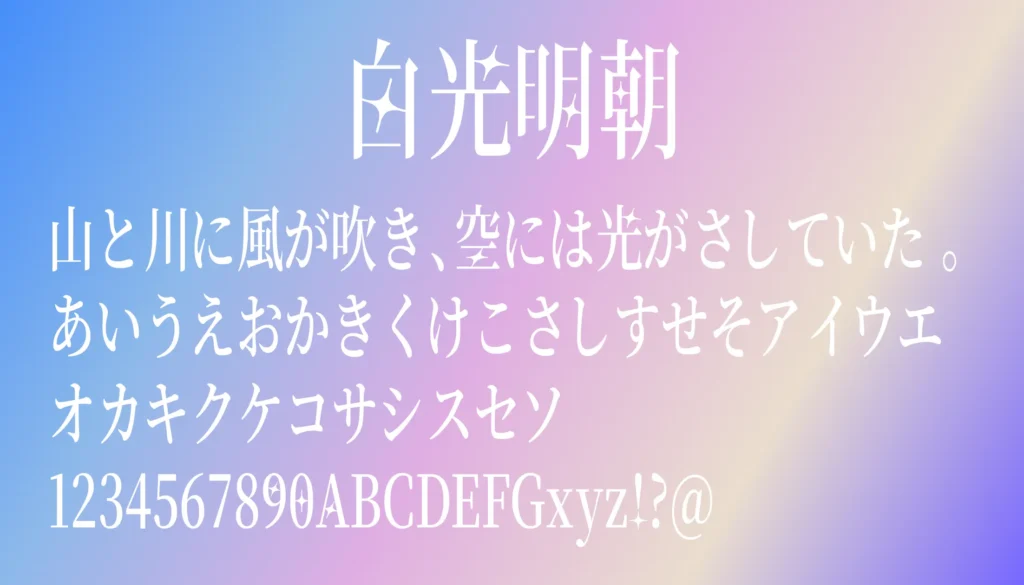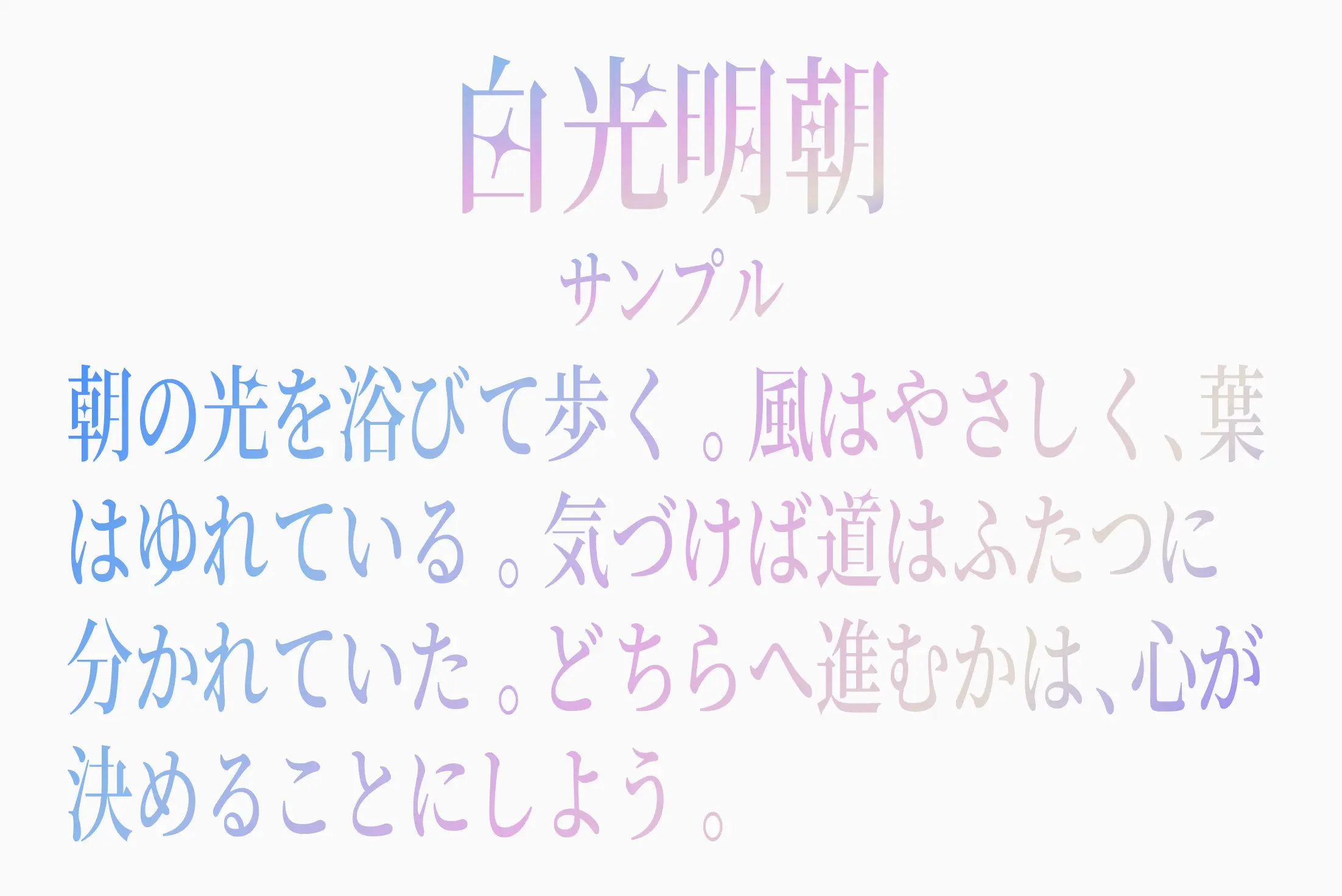
繊細に引き伸ばされた縦長シルエットと、きらめく星の装飾が印象的な明朝体フォントです。シャープな線の美しさと幻想的な世界観を両立しており、物語作品のタイトルや小説表紙、コスメブランド、MVサムネイルなどにぴったり。文字を並べるだけで透明感や神秘的な空気感を演出でき、静かで美しい余韻を残してくれます。商用利用にも対応しており、ロゴ制作やデザイン作品にも使いやすいフォントです。
白光明朝